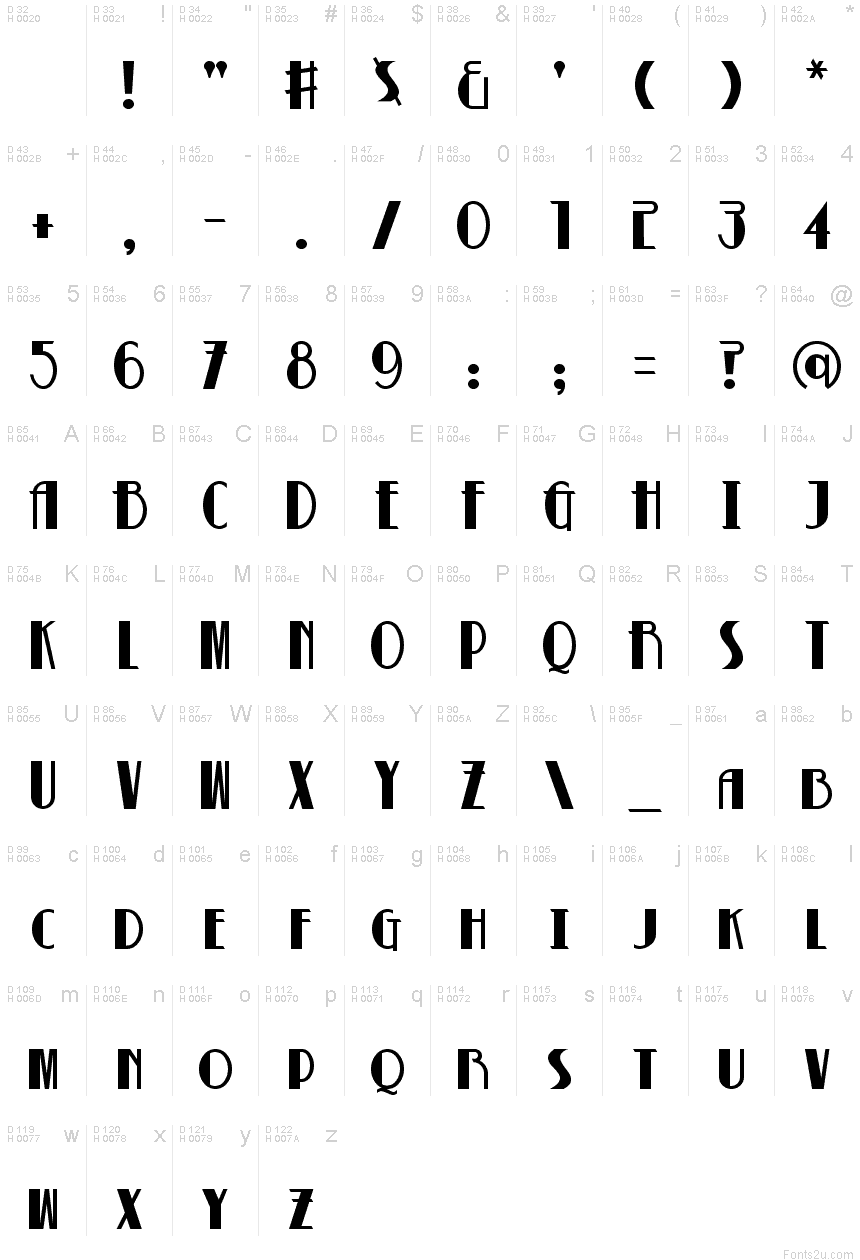
Betty Noir, stworzony przez Nate'a Piekosa z Blambot, to darmowy, retro krój displayowy, który przywodzi na myśl kinowy neon po zmroku. Wysokie, eleganckie litery z dynamicznymi łukami i wyrazistymi wycięciami nadają każdemu słowu klimat tajemniczego glamour w stylu Art Déco. Dzięki ciasnemu, zdecydowanemu światłu, Twoje nagłówki ułożą się niczym boldowe napisy na plakacie klasycznego kryminału lub vintage’owej reklamie klubu jazzowego.
Betty Noir pozwala błyskawicznie zbudować klimat na plakatach filmowych, okładkach książek, w menu koktajlowych, brandingu lokali typu speakeasy, zaproszeniach na wydarzenia czy opakowaniach w stylu retro. Ten darmowy font najlepiej prezentuje się w dużych rozmiarach, gdzie jego rzeźbiarskie kształty mogą w pełni zabłysnąć. Jako tekst uzupełniający warto dobrać czysty, geometryczny bezszeryfowy krój w mniejszym rozmiarze, aby utrzymać reflektory skierowane na ostry, kinowy charakter Betty Noir.